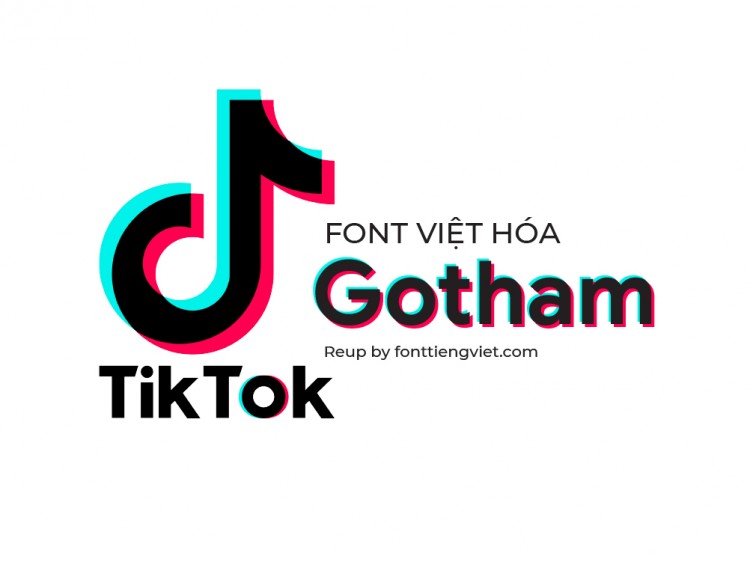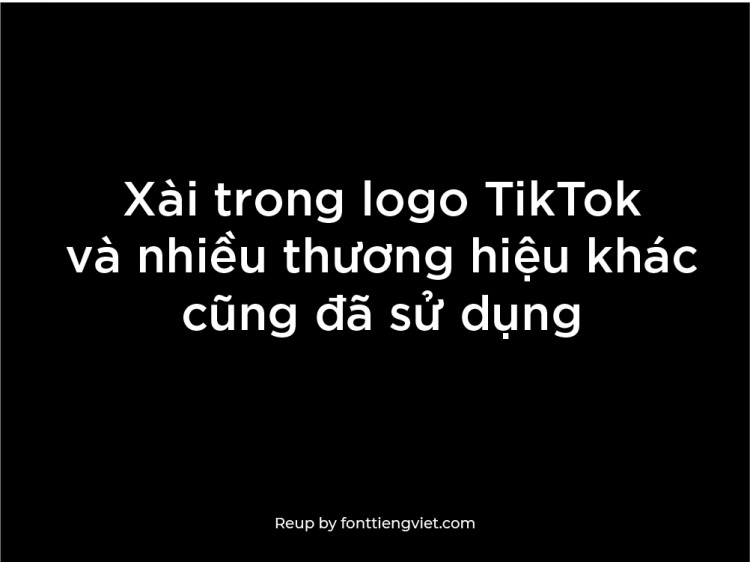
Tổng hợp 18 Font Gotham đẹp
Gotham là một trong những font chữ sans-serif mang tính biểu tượng, được yêu thích trong giới thiết kế nhờ vẻ đẹp hiện đại, đơn giản nhưng vô cùng mạnh mẽ. Ra đời vào năm 2000 bởi nhà thiết kế Tobias Frere-Jones và phát triển bởi Hoefler & Co., Gotham nhanh chóng trở thành lựa chọn hàng đầu cho các chiến dịch quảng cáo, truyền thông, và cả trong chính trị.
Đặc điểm nổi bật của Font Gotham
• Thiết kế cân đối: Gotham lấy cảm hứng từ các bảng hiệu kiến trúc tại thành phố New York trong thế kỷ 20. Các ký tự được thiết kế hình học với độ rộng đồng đều, mang đến cảm giác chắc chắn và dễ đọc.
• Tối giản nhưng sang trọng: Mặc dù là font sans-serif, Gotham không hề đơn điệu. Những chi tiết nhỏ được chăm chút kỹ lưỡng giúp font vừa tối giản vừa sang trọng, phù hợp với các thiết kế cần sự nghiêm túc, rõ ràng và chuyên nghiệp.
• Dễ đọc ở mọi kích thước: Nhờ tỷ lệ chữ hài hòa, font Gotham giữ được độ dễ đọc cả ở kích thước lớn lẫn nhỏ. Điều này lý tưởng cho các thiết kế web, app, in ấn, cũng như màn hình kỹ thuật số.
• Nhiều biến thể: Gotham có nhiều phiên bản như Gotham Bold, Light, Medium, Book, Black… và đi kèm chữ nghiêng (Italic) tương ứng, đáp ứng hầu hết các nhu cầu sử dụng trong thiết kế.
Ứng dụng phổ biến của Font Gotham
Font Gotham được sử dụng rộng rãi trong nhiều lĩnh vực:
• Thương hiệu & Nhận diện: Được dùng trong logo và bộ nhận diện của nhiều thương hiệu lớn như Spotify, Netflix, Coca-Cola (phụ trợ), và đặc biệt là chiến dịch tranh cử tổng thống Mỹ của Barack Obama năm 2008.
• Truyền thông & Chính trị: Vì tính chất tin cậy, nghiêm túc nên Gotham rất phù hợp với các chiến dịch chính trị, tổ chức phi lợi nhuận và tổ chức xã hội.
• Website & Ứng dụng: Với đặc điểm dễ đọc và đẹp ở mọi kích thước, Gotham là lựa chọn phổ biến cho giao diện UI/UX.
• Poster, tiêu đề, bìa sách: Gotham tạo cảm giác mạnh mẽ, hiện đại, rất lý tưởng cho các ấn phẩm quảng bá cần gây ấn tượng mạnh.
Font Gotham là đại diện tiêu biểu cho phong cách hiện đại, rõ ràng và chuyên nghiệp. Với thiết kế tinh tế, dễ đọc và đa dạng biến thể, Gotham xứng đáng là một trong những font chữ đáng có trong “kho vũ khí” của bất kỳ nhà thiết kế nào. Dù bạn đang xây dựng một thương hiệu mạnh, một giao diện web chỉn chu hay một poster ấn tượng thì Gotham luôn là một lựa chọn an toàn và đẳng cấp.